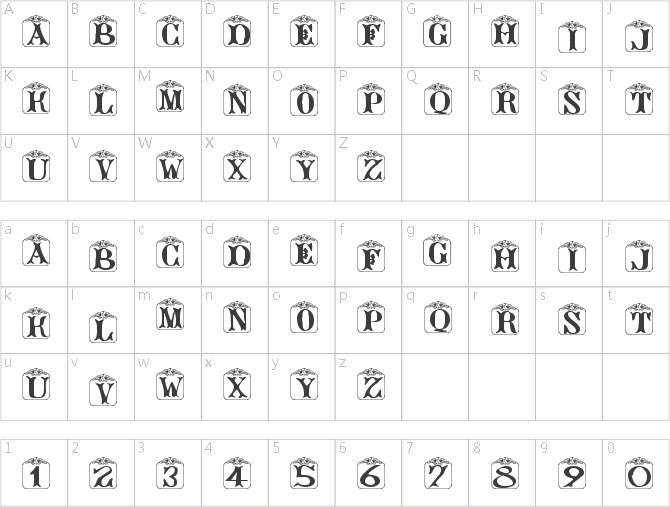
Angelots (Unregistered) 詳情頁
Angelots (Unregistered)字體字庫(kù)是一款讓人賞心悅目、百看不厭的英文字體,適合各類廣告和產(chǎn)品包裝設(shè)計(jì)應(yīng)用,字體大小0.03MB,格式為ttf字體,上傳用戶是晴朗,作者/版權(quán)方為未知